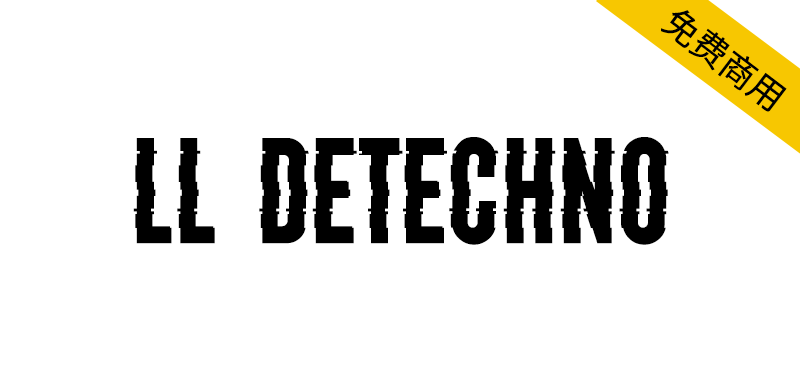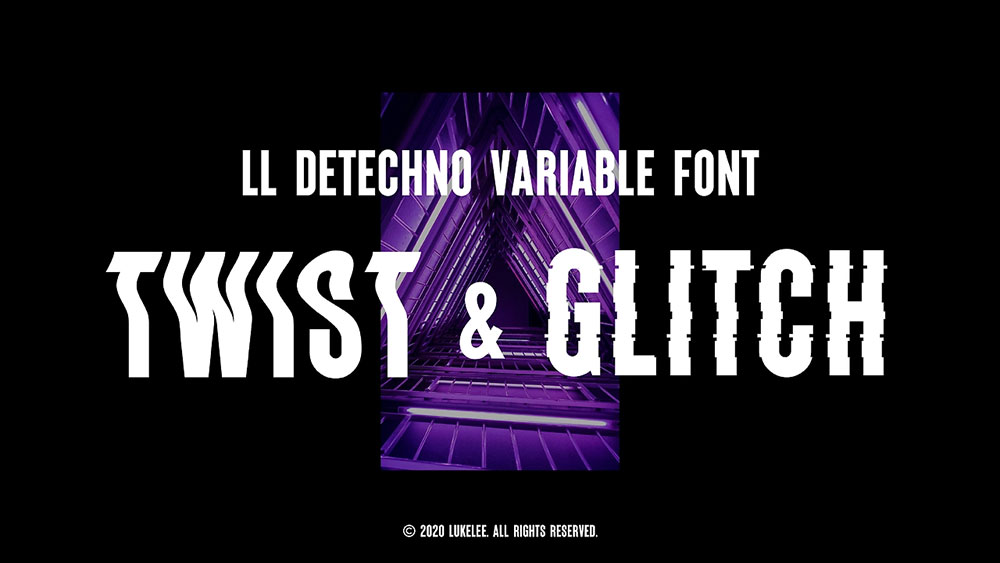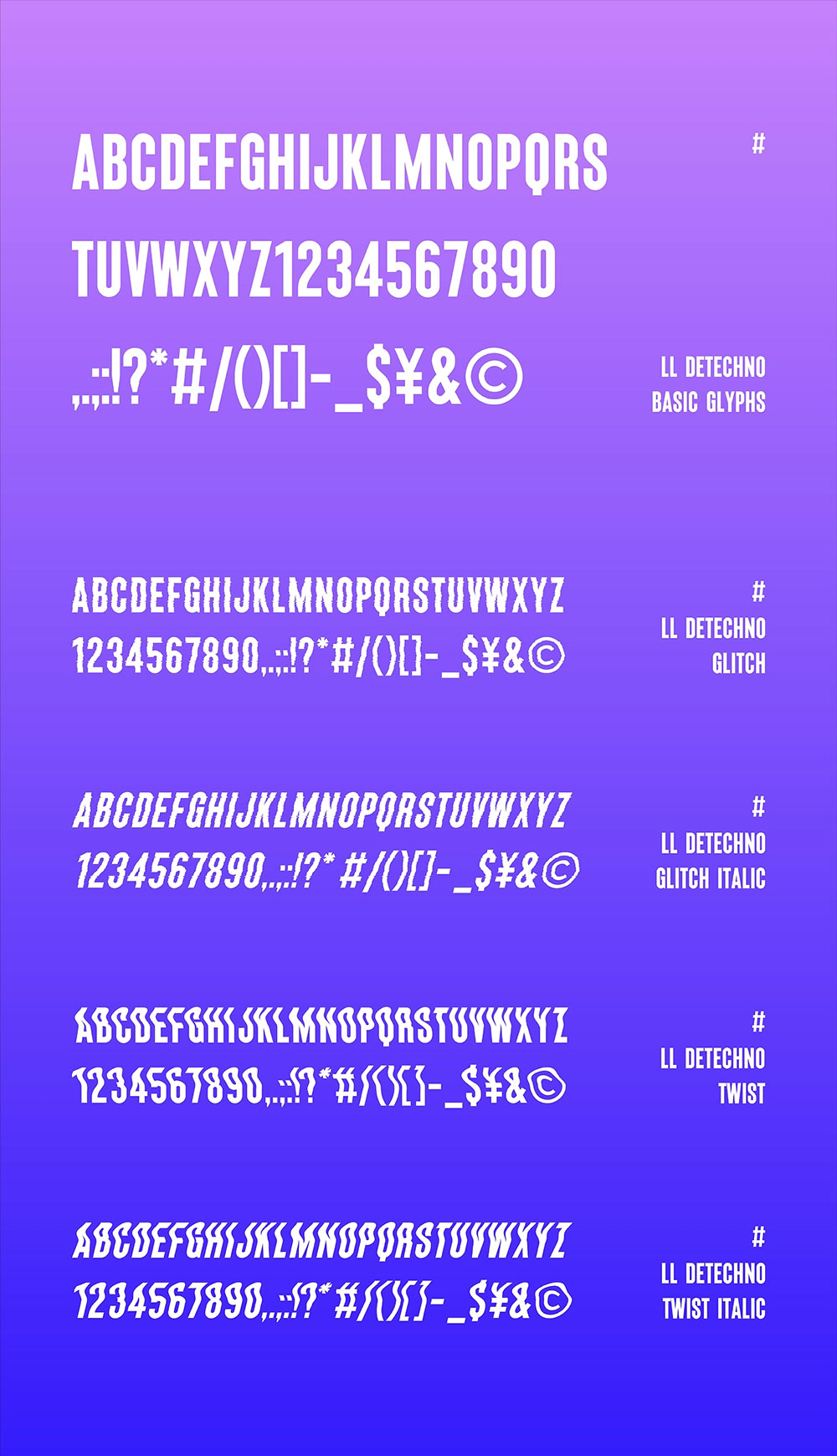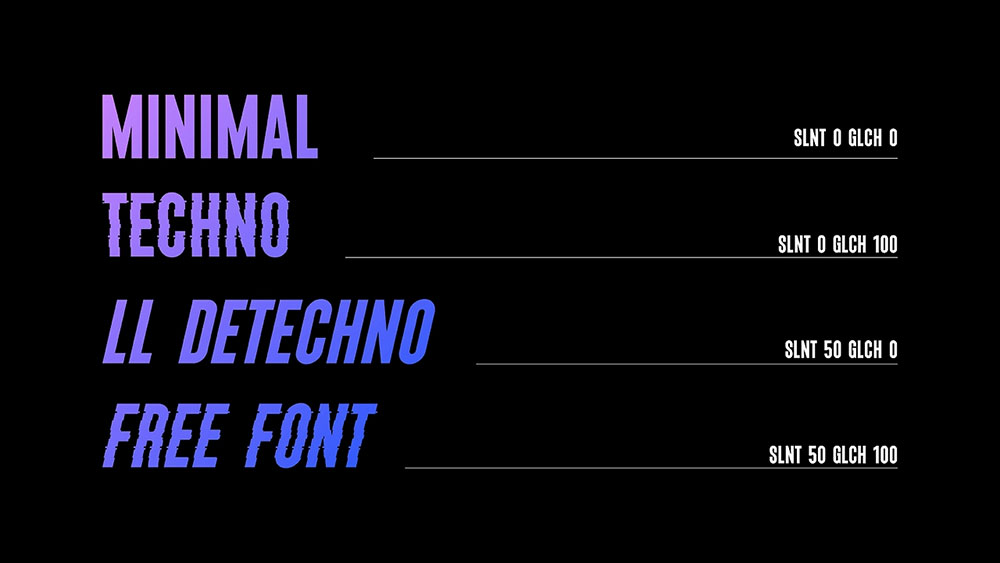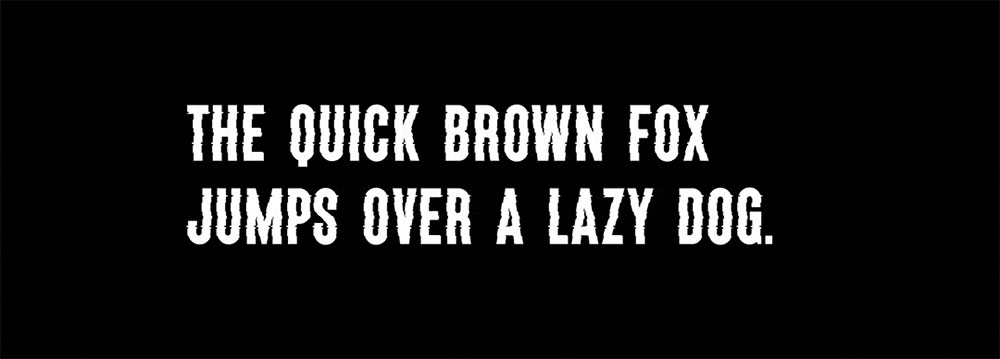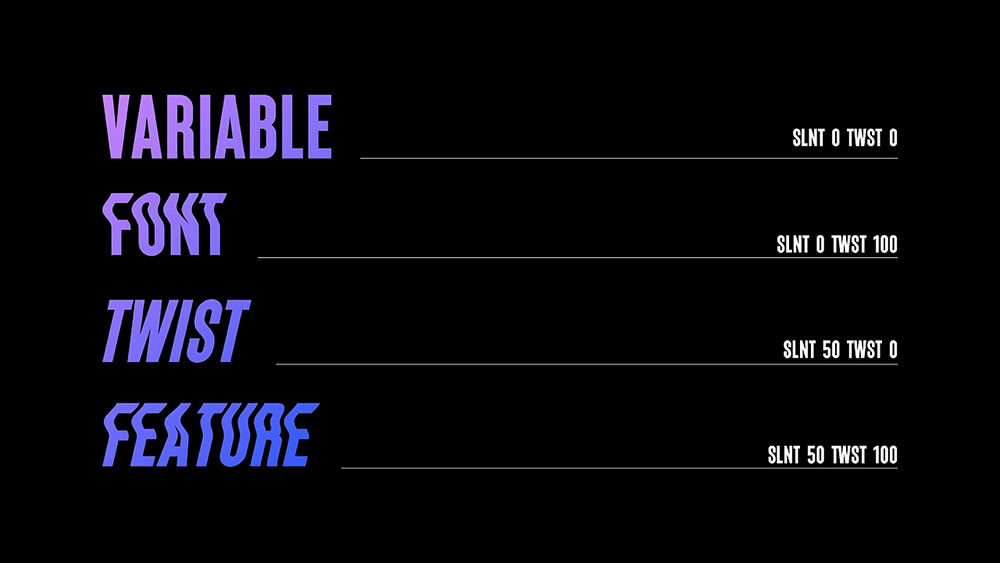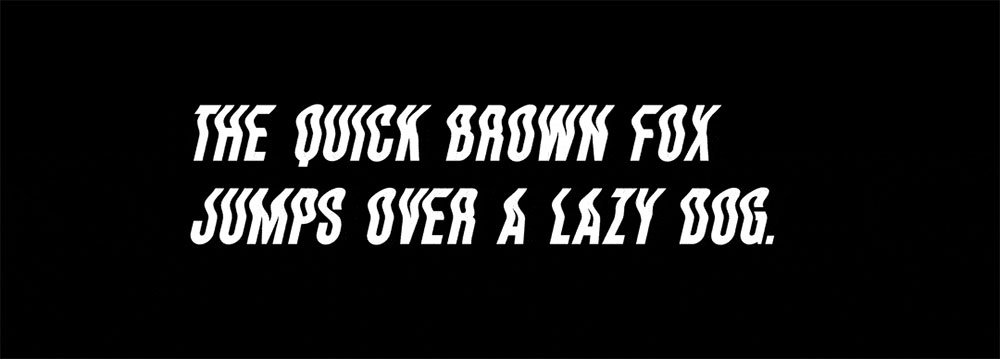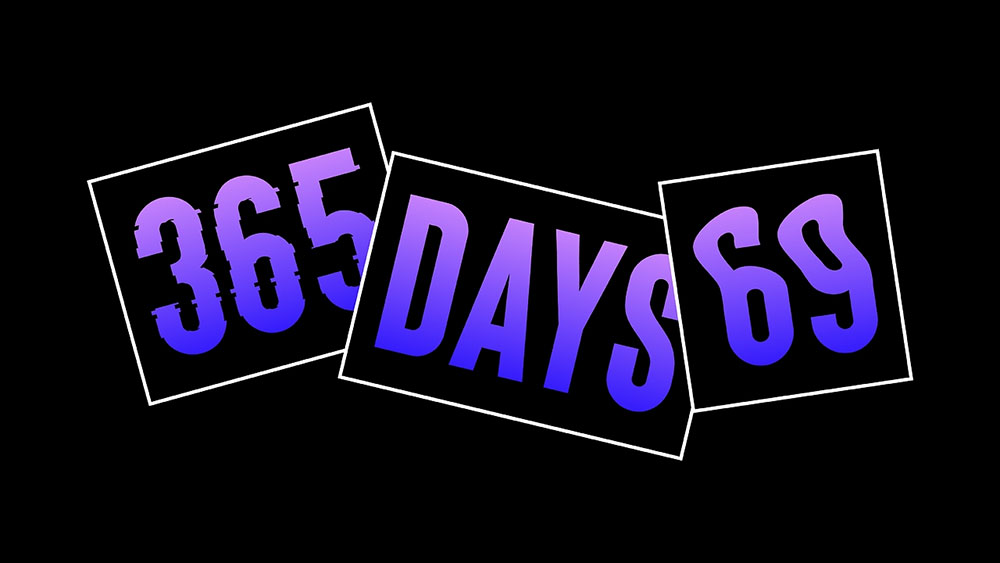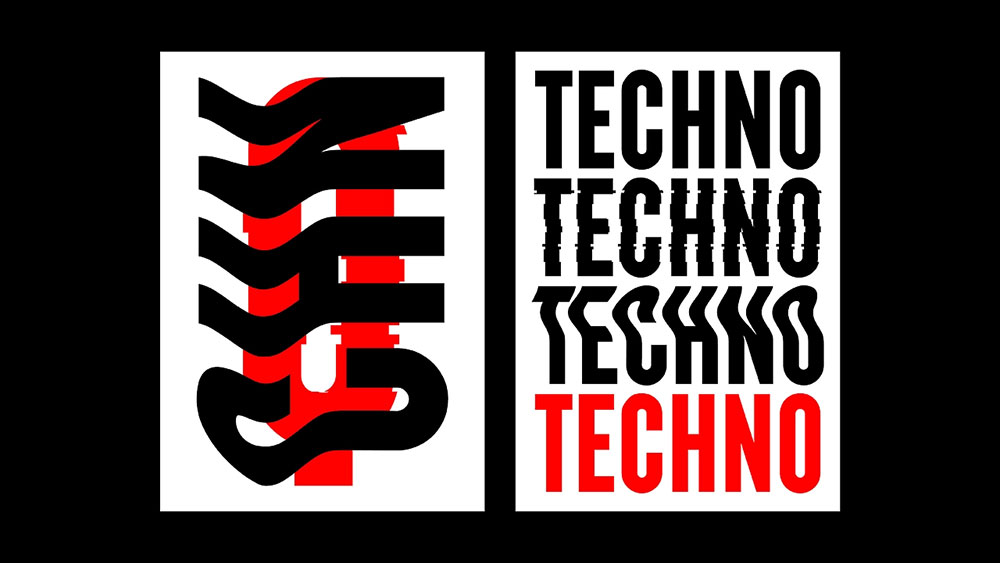
【LL DEtechno】具有扭曲和故障两种风格的英文标题字体
LL DEtechno这款字体灵感来源于每天听的Minimal Techno,Techno音乐简单直给的特点也体现在了这款字的基础字形中。加入可变特性的目的是想让这款字体可玩性更强,正好最近在研究可变,所以挑选了扭曲和故障两种风格进行字体的延展细化,给自己找找事儿干,同时增加这款字的可玩性。这款字更适合应用于标题,不推荐在正文中使用。同样这款字供各位免费使用,愿诸君用得开心,变形拉杆玩得痛快!